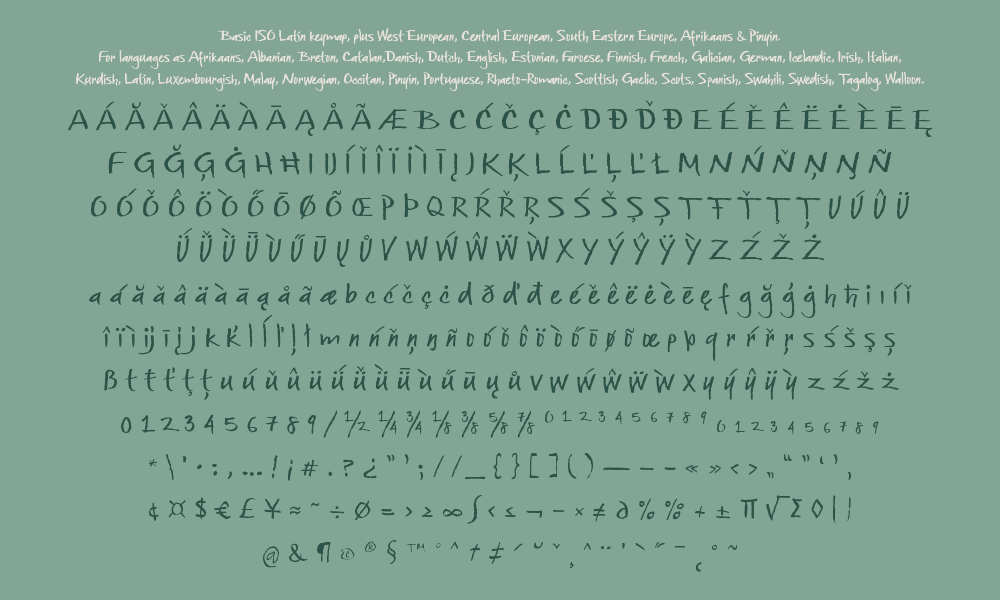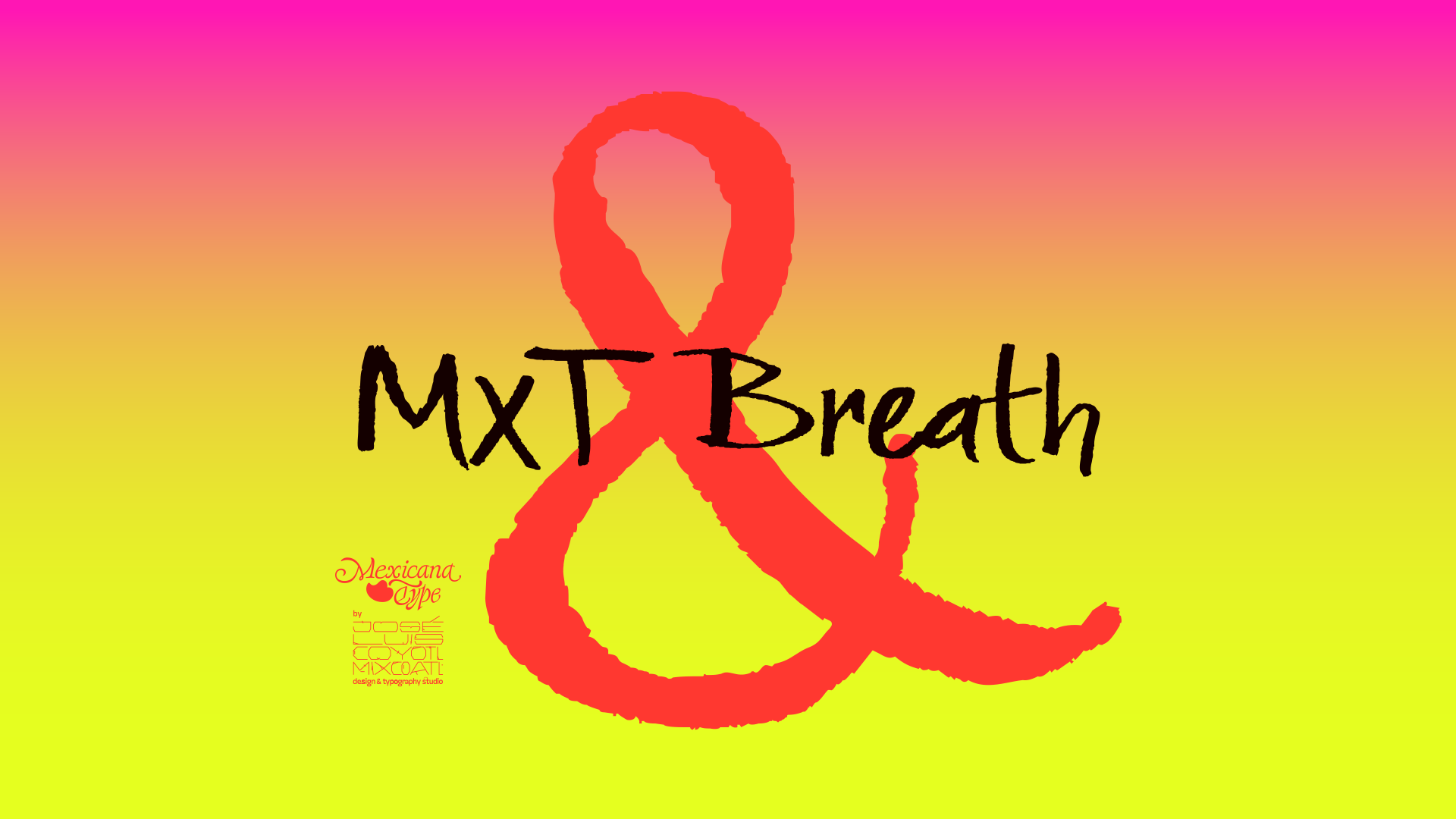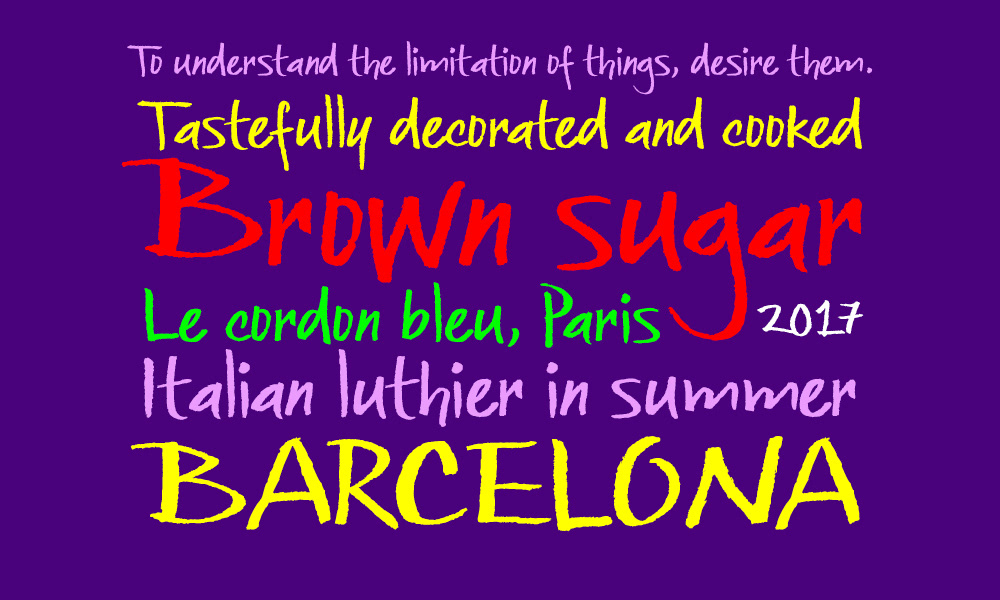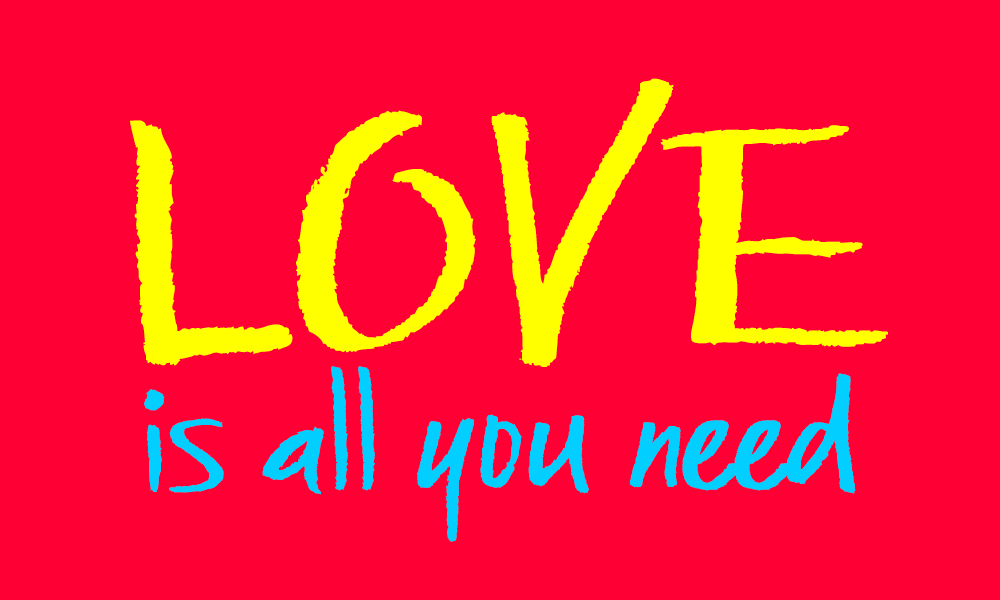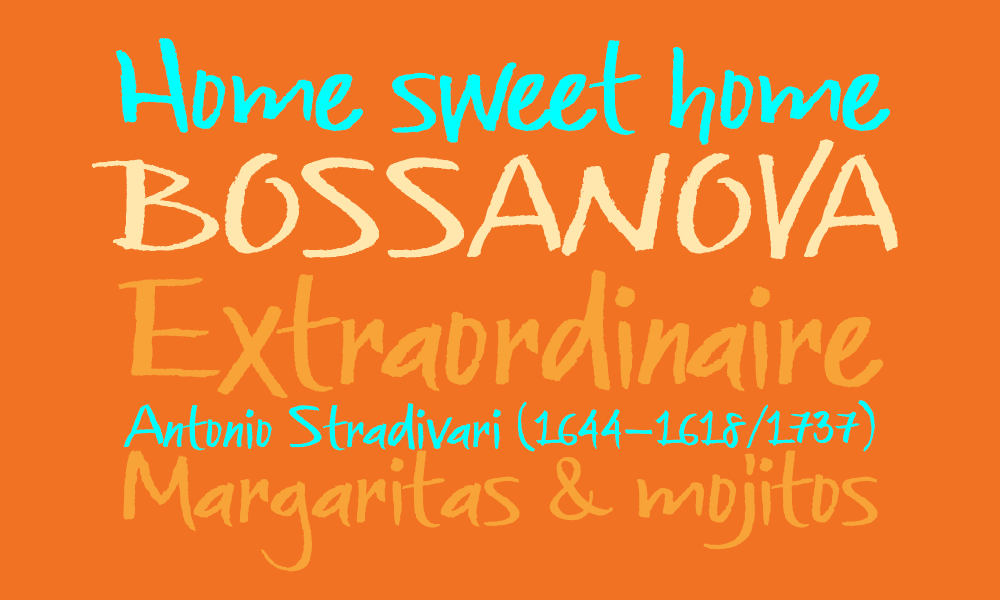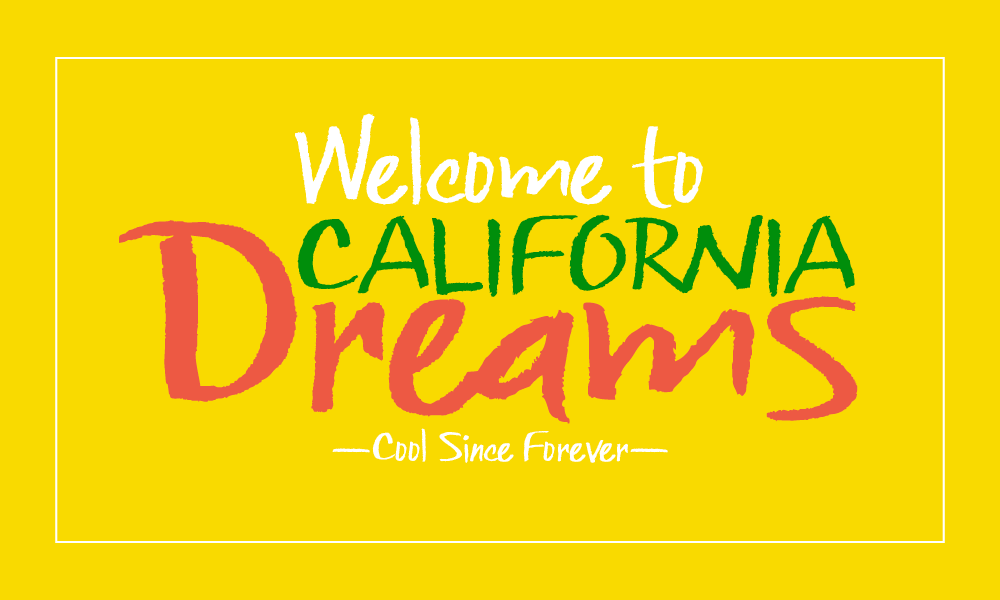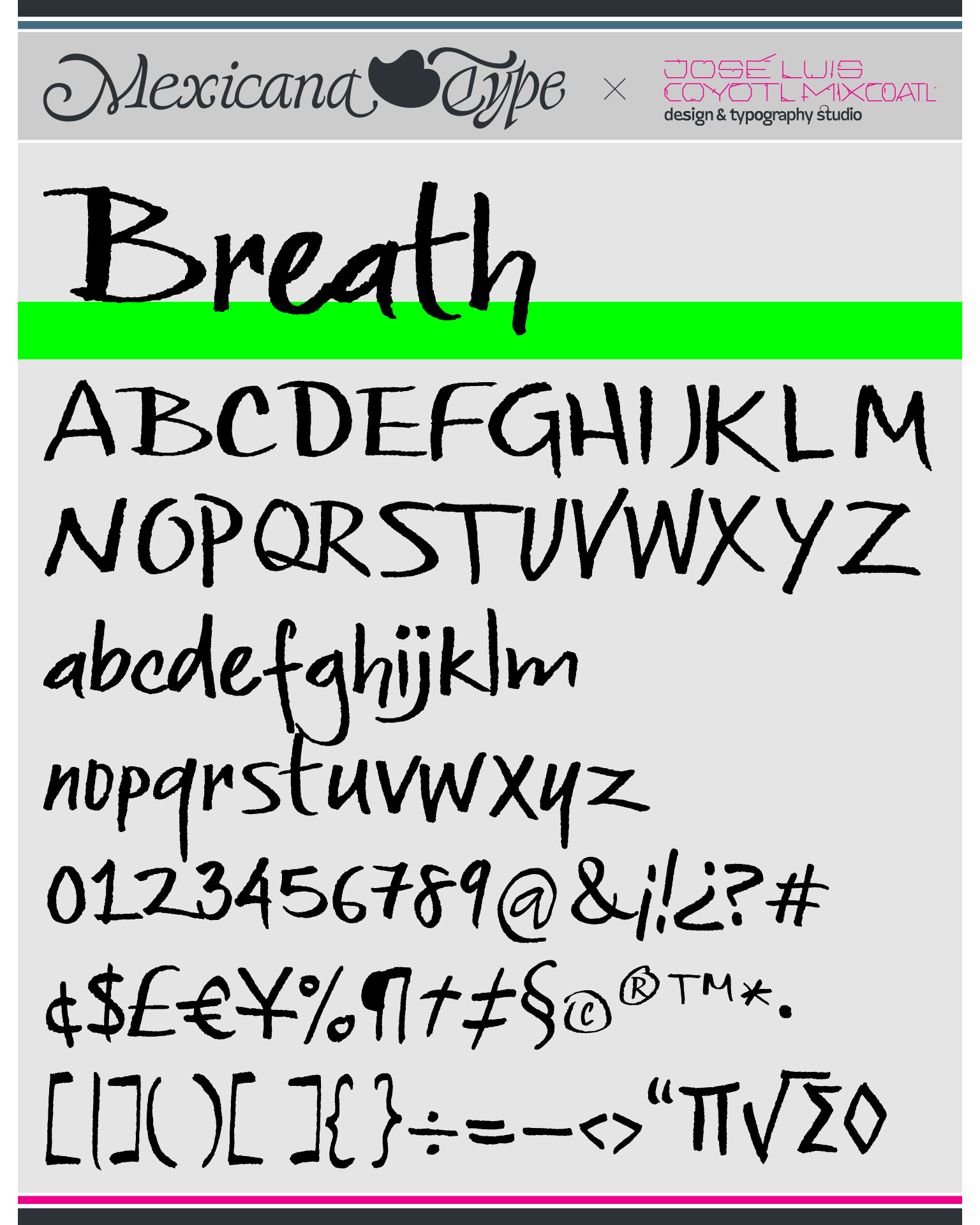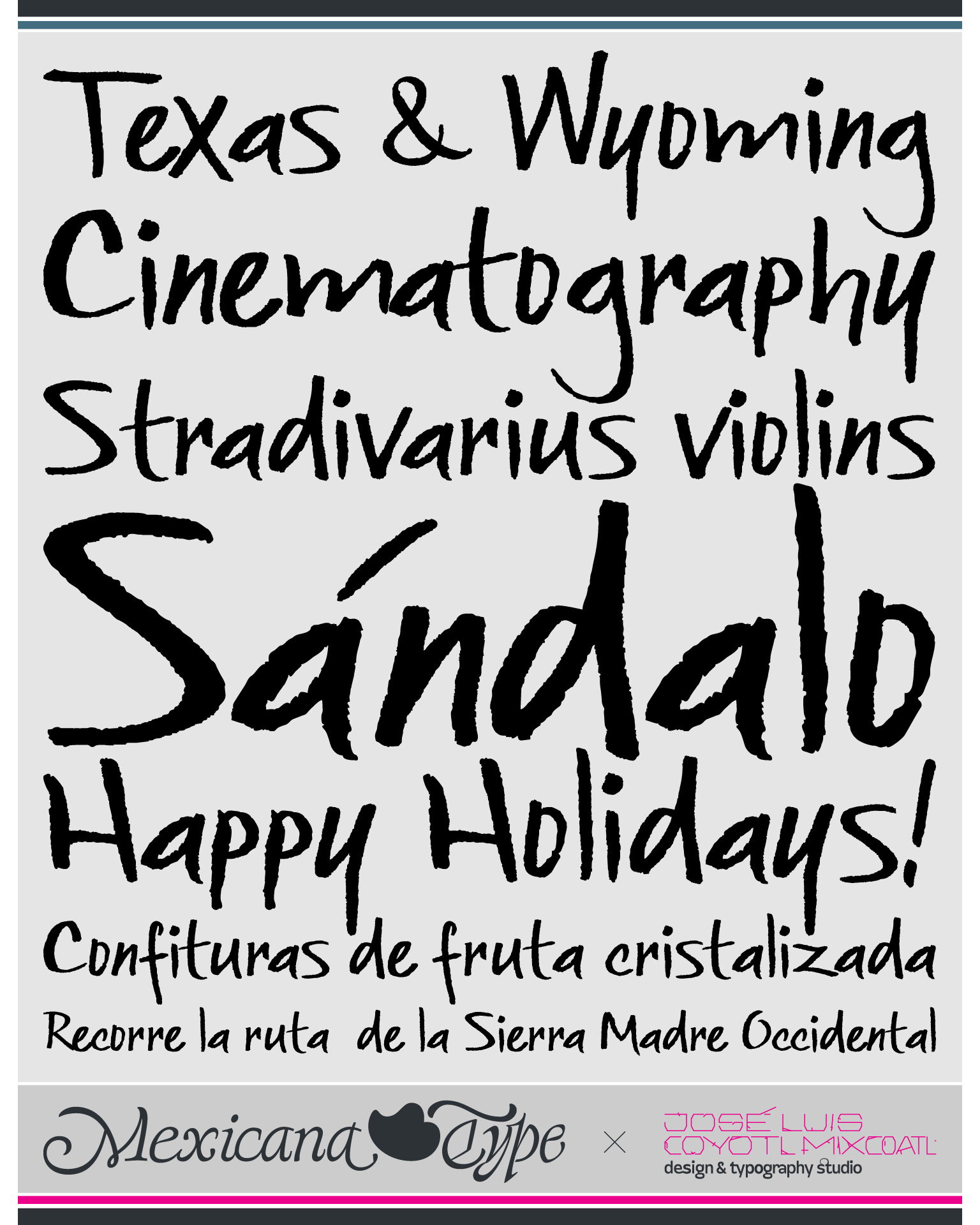
MxT Breath, fue desarrollada para un proyecto tipográfico personalizado. Para algunos titulares se necesitaba una tipografía de estilo manuscrito, libre y con aspecto desgastado, como dibujado a mano sobre una pizarra con textura de gis o de lápiz de cera. Ello generó una tipografía de forma orgánica y texturizada, sin tener una línea base y con un flujo asimétrico que transmite una sensación relajada logrando un estilo tipográfico gestual y relajado.